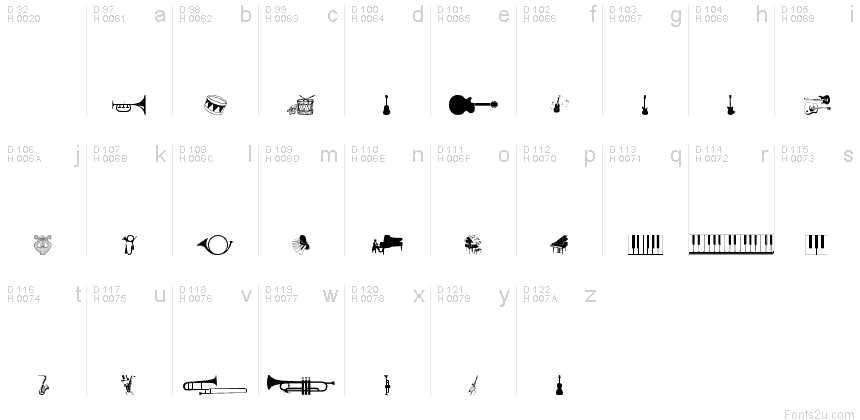
Wmmusic 1 to darmowy font typu dingbats, który zbiera klimat klubów jazzowych w zestaw zabawnych symboli. Motywy mocno osadzone w kulturze scenicznej – trąbka, saksofon w cylindrze, klawisze pianina i skrzydlate kształty klawiatur – mają masywne sylwetki, które wydają się dynamiczne, teatralne i nieco retro.
Pasuje naturalnie na plakaty koncertowe, ulotki z recitali, okładki albumów, programy imprez i materiały dla szkół muzycznych, gdzie darmowy font może zdziałać więcej niż zwykła ozdoba. Ponieważ rysunki czytają się jak wyraziste piktogramy, a nie przeładowane dekoracje, świetnie sprawdzają się w tytułach, separatorach sekcji i szybkich akcentach brandingowych w tematach jazzowych, fortepianowych czy związanych z występami na żywo.